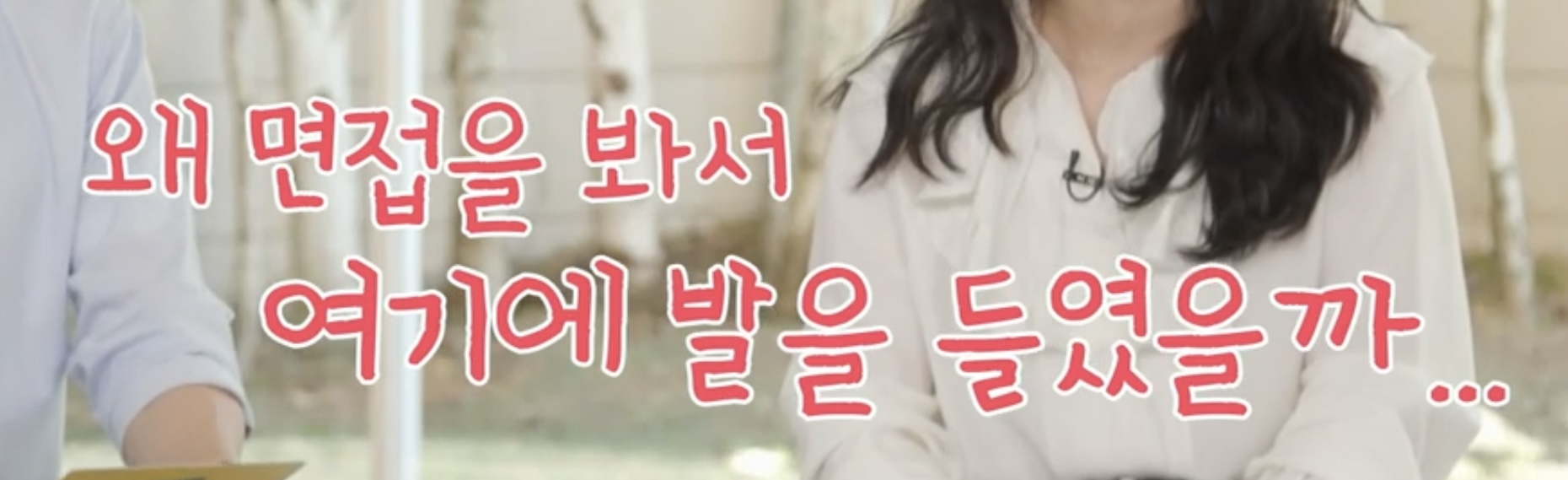
이 귀여운 폰트는 뭘까요,,, cut*** 2023.10.25 너무너무 궁금해요!! (출처 유퀴즈) 댓글 0 등록 sta*** 어비 남소영체 같네요 https://www.sandollcloud.com/font/16547.html 2023-10-26 답글 달기 댓글 더보기 쉽고 빠르게 가장 비슷한 폰트를 알고 싶다면? 이미지로 검색하기
어비 남소영체 같네요 https://www.sandollcloud.com/font/16547.html